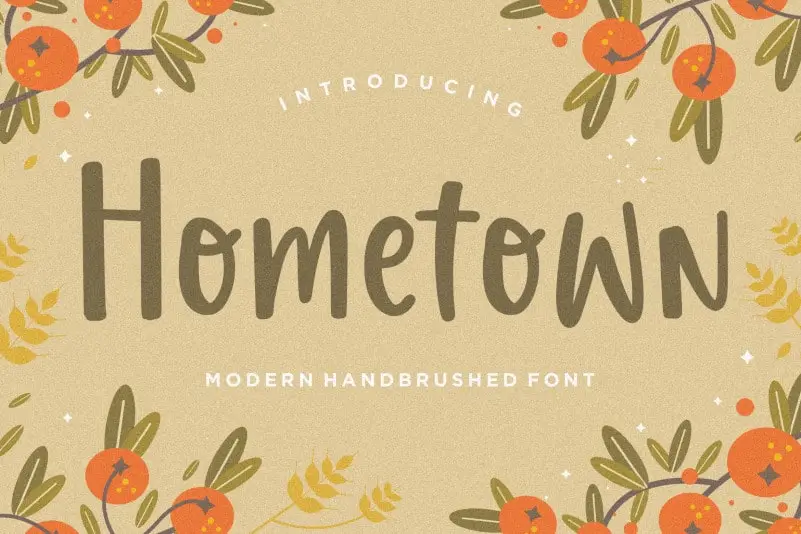
Hometown Display Font – Download Grátis
A fonte Hometown Display é perfeita para uma variedade de projetos, desde a embalagem de produtos até redes sociais e publicações de moda. Com seu design suave e elegante, esta fonte adquire um toque despojado ao mesmo tempo que mantém sua força e destaque nos materiais de comunicação visual. Suas formas arredondadas permitem uma escrita mais relaxada em cartazes ou redes sociais, enquanto suas linhas finas se destacam perfeitamente em embalagens de produtos. Esta fonte é ideal para criações de marca como revistas, jornais e até mesmo para celebrar um evento especial, como casamentos. Para os designers que buscam uma fonte versátil, a Hometown Display proporciona uma maneira interessante de expressar seus ideais criativos em qualquer projeto. Seja por sua simplicidade ou pela sua riqueza visual, ela é perfeita para quem busca mais do que apenas uma fonte: quer um elemento distintivo que pode dar aos projetos a personalidade necessária. A designer balpirick trouxe essa fonte à luz, oferecendo um toque de irreverência e leveza que faz dela uma opção muito interessante. A Hometown Display é mais do que uma ferramenta para escrita; ela é um ato de expressão. Seja no arco-íris da comunicação visual ou em qualquer outro lugar, este fonte se destaca como uma escolha inteligente para quem busca não apenas uma fonte, mas uma identidade visual única e envolvente.